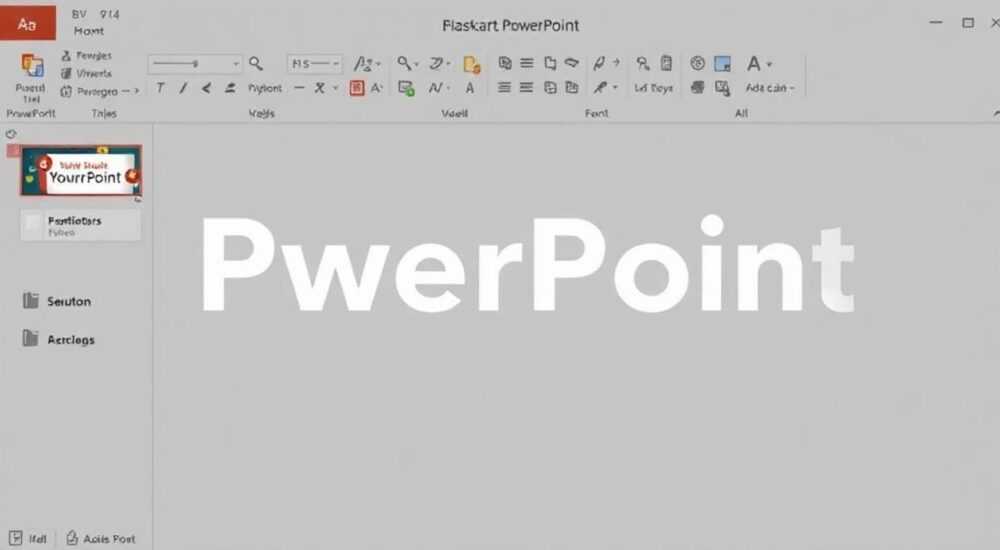
Как выбрать шрифт в повер поинт
Выбор шрифта в PowerPoint — это не просто вопрос эстетики, а важный элемент коммуникации. Правильно подобранный шрифт улучшает восприятие информации, усиливает воздействие презентации и помогает донести идею до аудитории. Неподходящий же может сделать даже содержательную работу визуально тяжелой, отвлекающей или даже непрофессиональной.
Чтобы выбрать правильный шрифт в PowerPoint, ориентируйтесь на контекст: используйте классические засечковые или беззасечковые шрифты для деловых презентаций, избегайте декоративных стилей в официальных материалах, и всегда проверяйте читаемость на экране.
Современные версии PowerPoint предлагают широкую библиотеку встроенных шрифтов, а также интеграцию с Microsoft 365 и онлайн-ресурсами, такими как Fonts.com. Однако обилие вариантов часто вызывает затруднения: какой шрифт выбрать для доклада, отчёта, презентации продукта или образовательного курса? Как сочетать гарнитуры, чтобы слайды выглядели целостно и профессионально? Ответы зависят от цели презентации, аудитории, темы и технических условий показа.
Основные типы шрифтов: как они влияют на восприятие
Шрифты делятся на несколько основных категорий, каждая из которых передаёт определённое настроение и подходит для разных задач. В PowerPoint важно понимать, как визуальные особенности шрифта влияют на восприятие текста аудиторией.
Беззасечковые (sans-serif) шрифты — такие как Calibri, Arial, Helvetica, Segoe UI — отличаются простотой и чистотой линий. Они легко читаются на экране, особенно при маленьком размере или на большом расстоянии. Идеальны для цифровых презентаций, выступлений, научных докладов и корпоративных материалов.
Засечковые (serif) шрифты — например, Times New Roman, Georgia, Cambria — имеют небольшие черточки на концах букв. Ассоциируются с традиционностью, академичностью и доверием. Часто используются в печатных материалах, но могут быть эффективны и в слайдах, если выбран подходящий размер и контраст.
Декоративные и рукописные шрифты — Comic Sans, Lobster, Pacifico — привлекают внимание своей уникальностью. Однако их стоит применять с осторожностью: они уместны только в неформальных, креативных или детских презентациях. В деловой среде такие шрифты могут вызвать недоверие.
Моноширинные шрифты — Courier New, Consolas — используются редко, главным образом для демонстрации кода, терминалов или технических данных. Их фиксированная ширина букв создаёт ощущение «машинописи».
Полезно знать: PowerPoint по умолчанию использует Calibri как системный шрифт с 2007 года, а с 2023 года в новых версиях Microsoft 365 он заменён на Aptos (бывший Bierstadt). Это беззасечковый шрифт, разработанный специально для цифрового чтения.
Как тип шрифта влияет на доверие и восприятие
Исследования в области нейромаркетинга показывают, что выбор шрифта влияет на уровень доверия к информации. Например, засечковые шрифты чаще ассоциируются с авторитетностью и точностью, тогда как слишком округлые или игривые формы могут снижать серьёзность сообщения.
В эксперименте Принстонского университета участники считали один и тот же текст более достоверным, когда он был набран шрифтом Baskerville, по сравнению с Comic Sans. Разница в восприятии достигала 13%.
• Для деловых встреч и инвестиционных презентаций предпочтительны строгие, нейтральные шрифты.
• Для образовательных и мотивационных выступлений допустимы более открытые и дружелюбные стили.
• В креативных индустриях можно экспериментировать, но важно сохранять баланс между оригинальностью и функциональностью.
Как выбрать шрифт для презентации: ключевые критерии
Выбор шрифта начинается не с внешнего вида, а с анализа контекста. Вот пять основных факторов, которые нужно учитывать:
• Цель презентации: информирование, убеждение, обучение или продажа?
• Аудитория: коллеги, клиенты, инвесторы, студенты?
• Формат показа: проектор, большой экран, мобильное устройство?
• Тема и стиль: техническая, художественная, финансовая, образовательная?
• Единый фирменный стиль: есть ли у компании гайдлайн по шрифтам?
Например, презентация для медицинской конференции требует максимальной ясности и профессионализма. Здесь подойдут шрифты типа Segoe UI или Lato. А для запуска нового продукта в сфере дизайна можно использовать современный геометрический sans-serif, например Montserrat или Raleway.
Полезно знать: чем дальше зритель от экрана, тем крупнее должен быть шрифт. Минимальный рекомендуемый размер для заголовков — 28 pt, для основного текста — 18–24 pt.
Когда использовать засечковые, а когда — беззасечковые шрифты?
Раньше считалось, что засечковые шрифты лучше читаются в печати, а беззасечковые — на экране. Современные исследования и улучшенная ретина-графика частично опровергают это, но правило остаётся актуальным для большинства случаев.
Тип шрифта
Где использовать
Примеры
Беззасечковые
Онлайн-презентации, выступления, корпоративные слайды